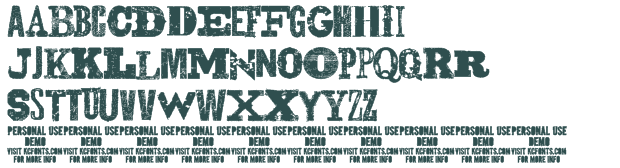
Gunslinger und Slopy ersetzen
Leider haben die Gunslinger und die Floppy keine Umlaute. Hat jemanden eine Idee  durch welche Fonts diese ersetzen könnte??
Magst Du hier mal Bilder der Schriften zeigen, die Du ersetzen willst? Ich kenne beide Schriften den Namen nach nicht und habe nicht die Zeit, jetzt im Netz zu suchen. Aber wenn Du Abbildungen hier einstellst, dann fallen mir oder Kollegen dazu vielleicht spontan Ersatzschriften ein.
Ist die Gunbslinger so ein "Zwiebelfischsuppen-Font" aus verschiedensten, teils Western-Schriften, die alle so ein bischen Abgenudelt aussehen? Also eine Schriftart, die diesen "Erpresserbrief-Effekt" hat?
Und ich hatte ja auch nicht behauptet, dass der Fragesteller die Demoversion hätte, sondern das es IM NETZ eben diese gibt, dabei aber dann eben die Kontaktadrese gibt, und da könnte man ja auch nach Umlauten fragen, denn diese zu erstellen dürfte ja für den Font-Autor keine unlösbare Aufgabe sein, wenn dafurch ein Verkauf zu Stande kommt.
Leider [hat] die Gunslinger […] keine Umlaute.
Was siehst du denn, wenn du »ÄÖÜäöü« in der dir vorliegenden Kopie der Gunslinger setzt? Ist es ein Platzhaltertext (in der aktuellen Dafont-Version »KC FONTS«), dürfte es sich um eine Demo- bzw. aus anderen Gründen abgespeckte Version handeln.
Ist die Sloppy so eine, etwas ungelenke Handschrift? das ist das einzige, dass ich unter diesem Namen gefunden habe.